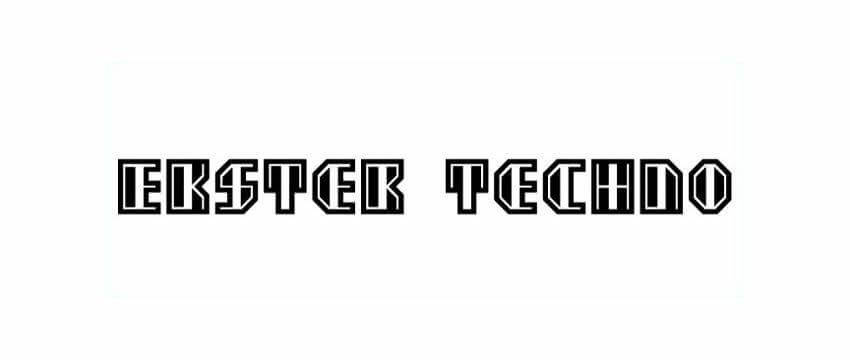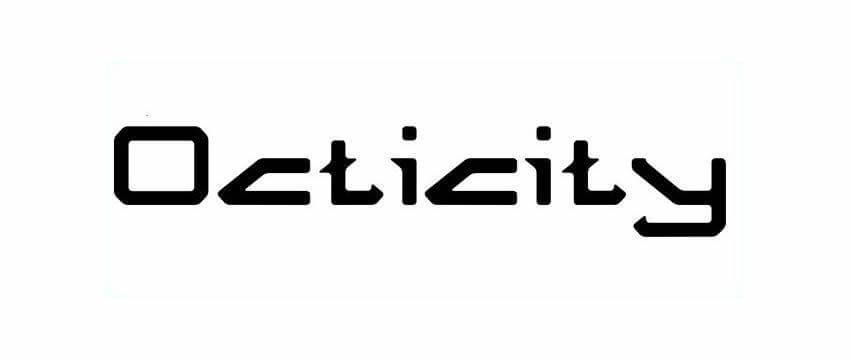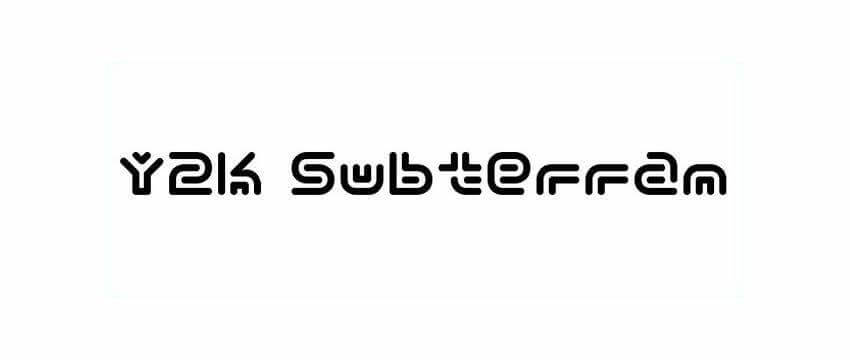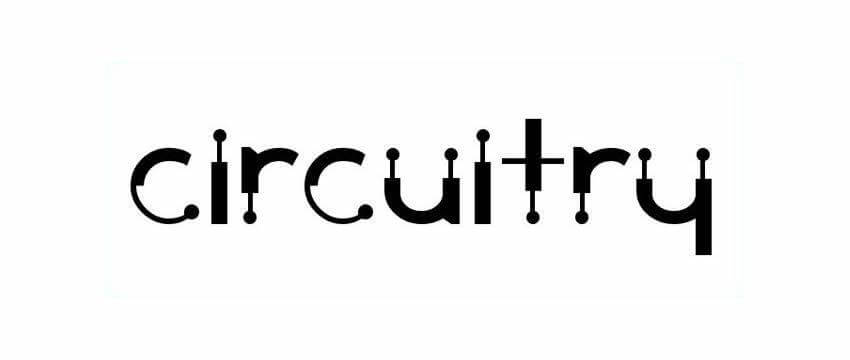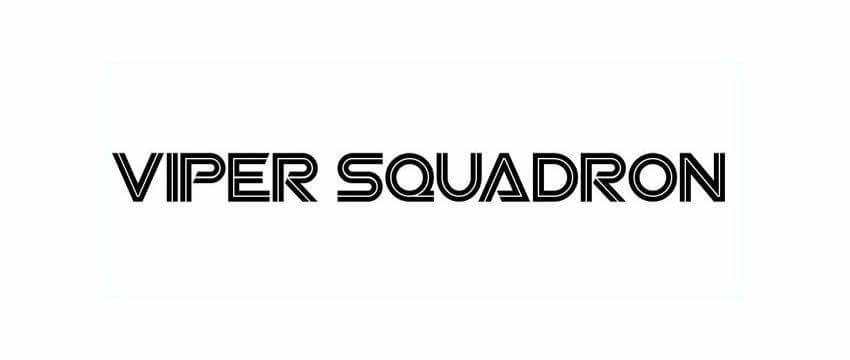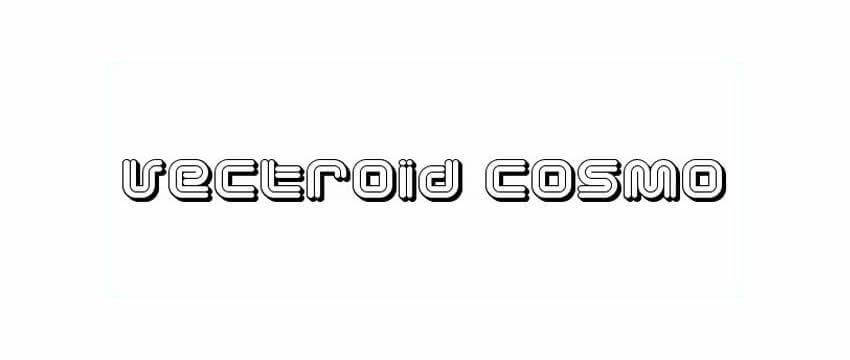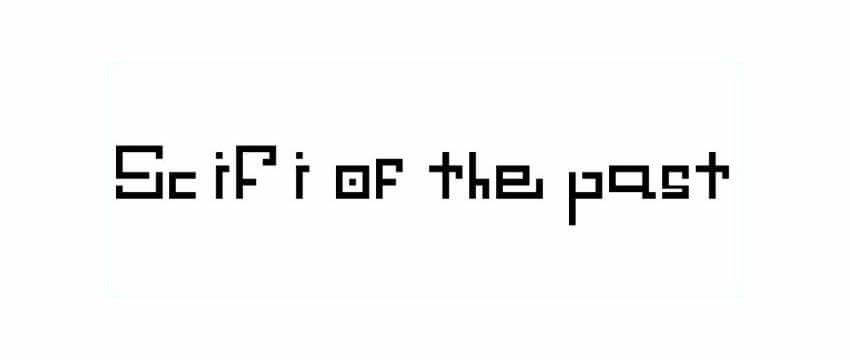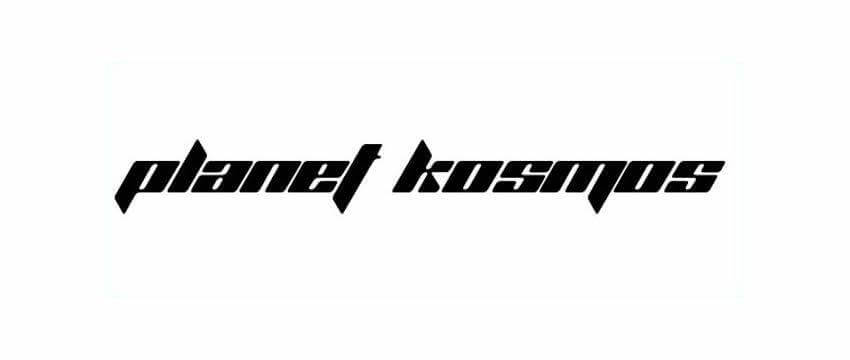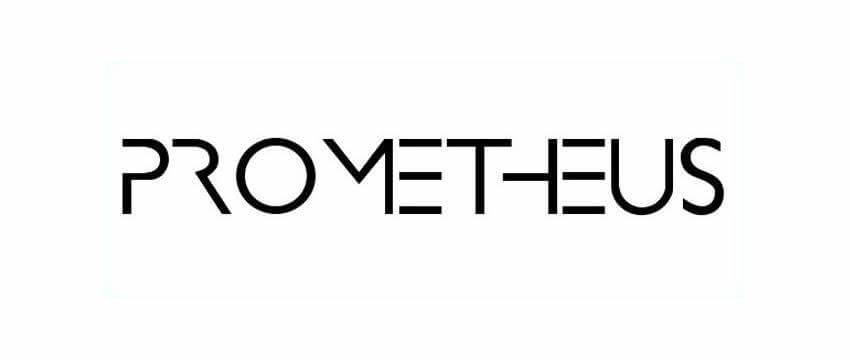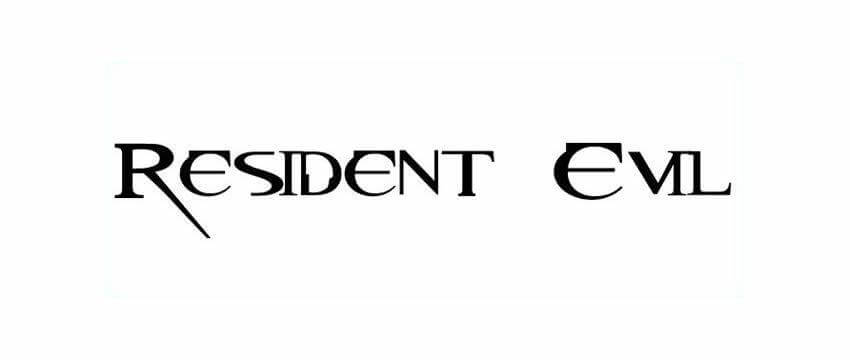
魅力的なテクノ&SF無料フォント25選―自分のデザインにも未来のルックスを取り入れよう!
フォントがデザインを左右するという事実は間違いありません。ほとんどの場合、フォントはデザイン全体のトーンを設定するため、フォントの選択には特別な注意を払う必要があります。
プロジェクトに適したフォントを選択する際には、フォントの見た目や使い心地から、フォントが他のフォントとどのように機能するか、さまざまなサイズでのフォントの読みやすさ、使用場所など、考慮すべきことがたくさんあります。実際に適切なフォントを選択する行為が、よく科学的だと感じることがあります。
そのため、自分のデザイナーツールボックスでは、さまざまなフォントやフォントスタイルを自由に使用できることが不可欠です。これは、プロジェクトに適したフォントを簡単に見つけるための最良の方法なのです。
フォントの中で人気のあるカテゴリは、独特な見た目/感覚が特徴的なテクノフォントとSFフォントです。人気のあるフォントタイプですが、使用に最適なのは、ゲームインターフェイス、SF雑誌、未来的なイベントやテクノをテーマにしたイベントを宣伝するために使用される本やポスターなどのプロジェクトです。
このまとめでは、あなたのデザインプロジェクトでも使用できる、ウェブ上のベストテクノフォントとSFフォントを集めました。以下に、円形または正方形の文字形式の幾何学的フォント、レトロフューチャーフォント、その他多くのフォントを載せました。それらはさまざまなプロジェクトで使用でき、何よりも無料であるため、自分のおサイフと相談する必要なしです!私たちのコレクションをチェックして、複数の素晴らしいテクノフォントとSFフォントを楽しんでください。
Eksterテクノフォント(無料)
SF Boxフォント(無料)
Octicityフォント(無料)
Y2k Subterranフォント(無料)
Circuitryフォント(無料)
Viper Squadronフォント(無料)
Vectroid Cosmoフォント(無料)
SciFi-of-the-Pastフォント(無料)
Planet Kosmosフォント(無料)
Prometheusフォント(無料)
Resident Evilフォント(無料)
Sci-Fied Bitmapフォント
サイエンスフィクションフォント(無料)
サーキットボードフォント(無料)
Coalitionフォント(無料)
Neutroniumフォント(無料)
BloodWaxフォント(無料)
Ethnocentricフォント(無料)
TRONフォント(無料)
ターミネーターリアルフォント(無料)
Vtks Rude Metalフォント(無料)
Robotaurフォント(無料)
Space Ageフォント(無料)
Dream MMAフォント(無料
Perfect Darkフォント(無料)